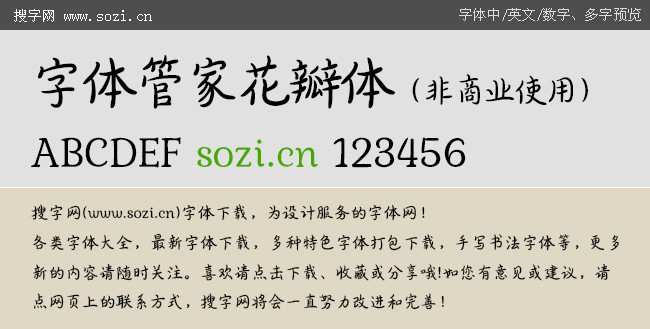
字體管家花瓣體(非商用版)
搜字網(wǎng)給大家提供一款字體管家花瓣體(非商用版)中文字體下載,該字體是一款手寫中文字體,這款字體字形瀟灑大方,干凈利落,適合包裝設(shè)計(jì)、書裝設(shè)計(jì)、海報(bào)設(shè)計(jì)等應(yīng)用(此字體為個(gè)人非商用版,商用可以聯(lián)系QQ:1006760504)。